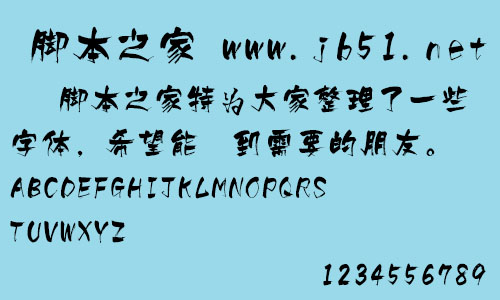
飛白體是一款中文字體,字體筆觸粗實(shí)且清晰,字體靈動(dòng)、瀟灑且飄逸,優(yōu)雅且優(yōu)美,適合應(yīng)用于藝術(shù)設(shè)計(jì)、平面宣傳設(shè)計(jì)、網(wǎng)頁設(shè)計(jì),書法字帖等領(lǐng)域,需要的朋友可以前來本站下載。
書法中運(yùn)用飛白,體現(xiàn)出一種藝術(shù)美
首先,運(yùn)用飛白會(huì)產(chǎn)生筆畫美。倘若飛白運(yùn)用得好,有的筆畫似流星劃過蒼穹,有的如快艇急馳水面,有的如懸崖瀑布飛縱,有的像織布細(xì)線伸展,有的若女子秀發(fā)隨風(fēng)飄動(dòng)……真是千姿百態(tài),美不勝收。
細(xì)觀古代書家所運(yùn)用的飛白,在其強(qiáng)烈的書法風(fēng)格中都蘊(yùn)含著怡人的筆畫美:王羲之的飛白楚楚動(dòng)人,王獻(xiàn)之的飛白顧盼生姿,顏真卿的飛白酣暢純厚,歐陽詢的飛白嚴(yán)謹(jǐn)險(xiǎn)勁,趙孟頫的飛白清麗秀逸,米芾的飛白痛快淋漓,懷素的飛白瀟灑自如……
其次,運(yùn)用飛白可使單字增輝不少。單字中的飛白和其他筆畫虛實(shí)相生,具有圖畫美,間或具有裝飾美。有時(shí),單字中的其他筆畫寫得平淡無奇,若恰當(dāng)運(yùn)用飛白,可使該字頓時(shí)搶眼;有時(shí),飛白還可掩蓋或挽救一字中不明顯的敗筆,收到轉(zhuǎn)移著眼點(diǎn)的效果;有時(shí),在單字的某豎畫中恰當(dāng)運(yùn)用飛白,以求得相對(duì)穩(wěn)定,達(dá)到欹不失正、正中寓欹的平衡效果。
此外,上述飛白之美體現(xiàn)在一幅書法作品中,無不有利于產(chǎn)生整體美。整幅作品中的飛白,有的如山澗一泓清泉,清新自然;有的似花朵零星點(diǎn)綴少女衣裙,款款生情;還有的像孩童在母親懷里玩耍,富有,等等。值得一提的是,在飛白的輕重徐疾中,可以反映出書寫的節(jié)奏,這也是增強(qiáng)作品整體美的表現(xiàn)之一。